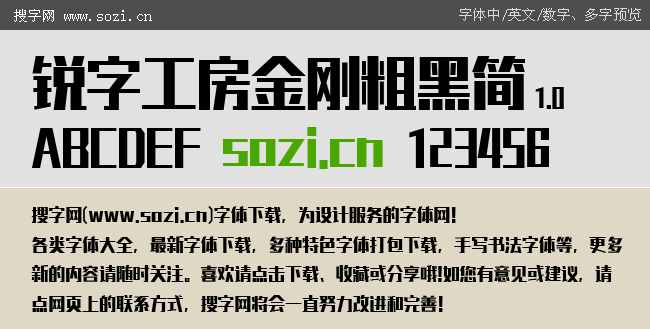
銳字工房金剛粗黑簡(jiǎn)1.0
搜字網(wǎng)提供一款非常藝術(shù)的黑體銳字工房金剛粗黑簡(jiǎn)1.0下載,銳字工房金剛粗黑簡(jiǎn)是一款字形方正的銳字工房字體,該字體極具藝術(shù)感,簡(jiǎn)潔大方,適用于包裝印刷、廣告設(shè)計(jì)、平面設(shè)計(jì)、書(shū)籍報(bào)紙等領(lǐng)域。
- 風(fēng)格類(lèi)別: 現(xiàn)代藝術(shù)體